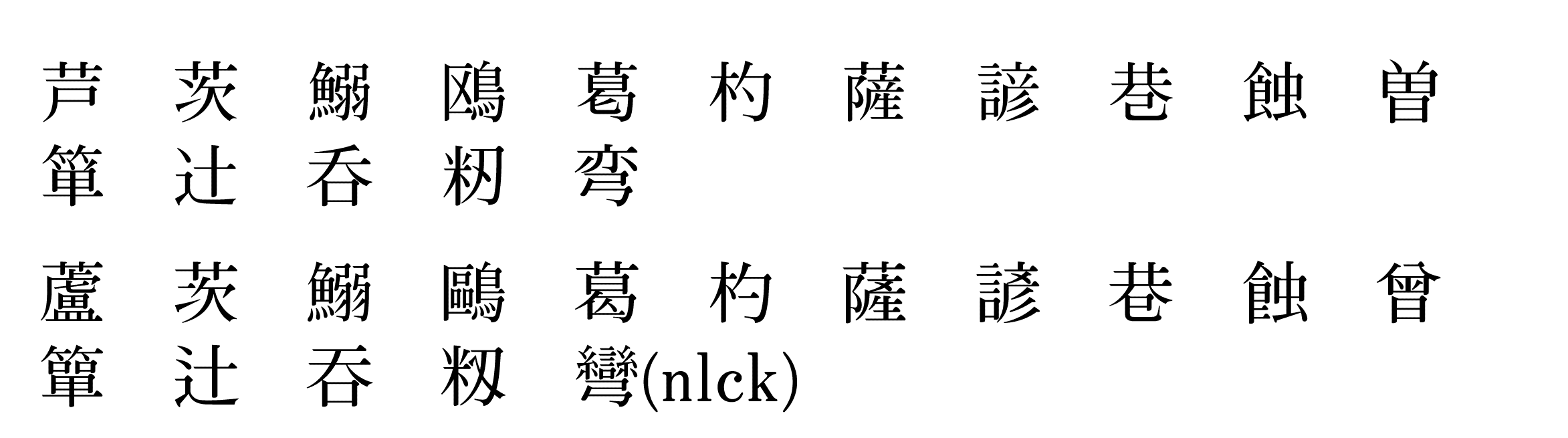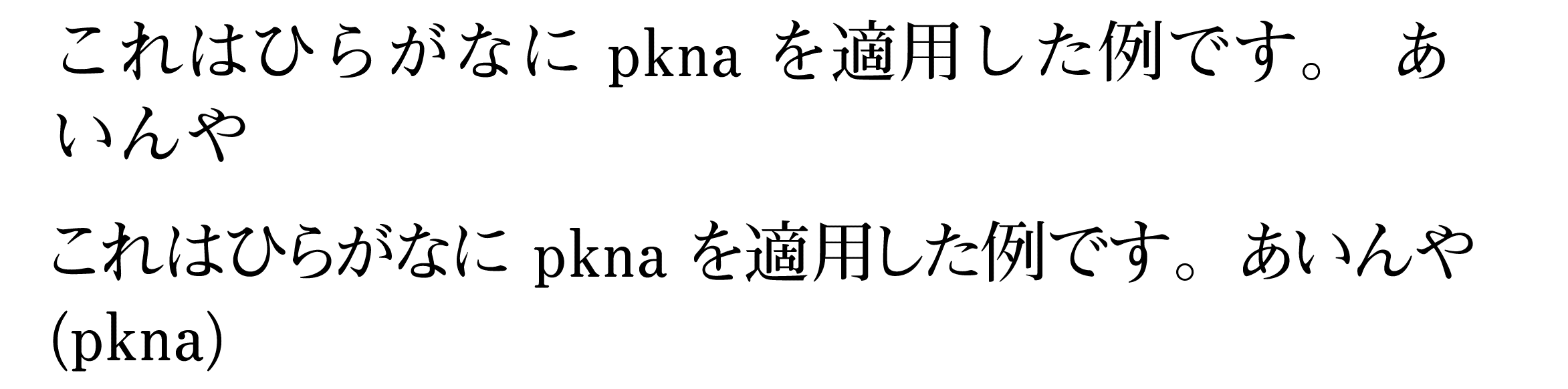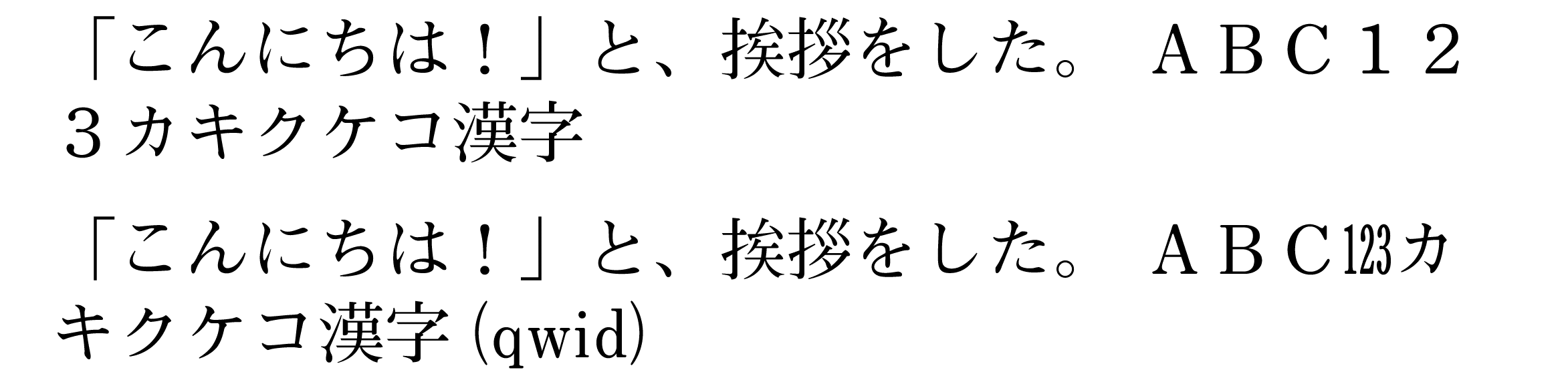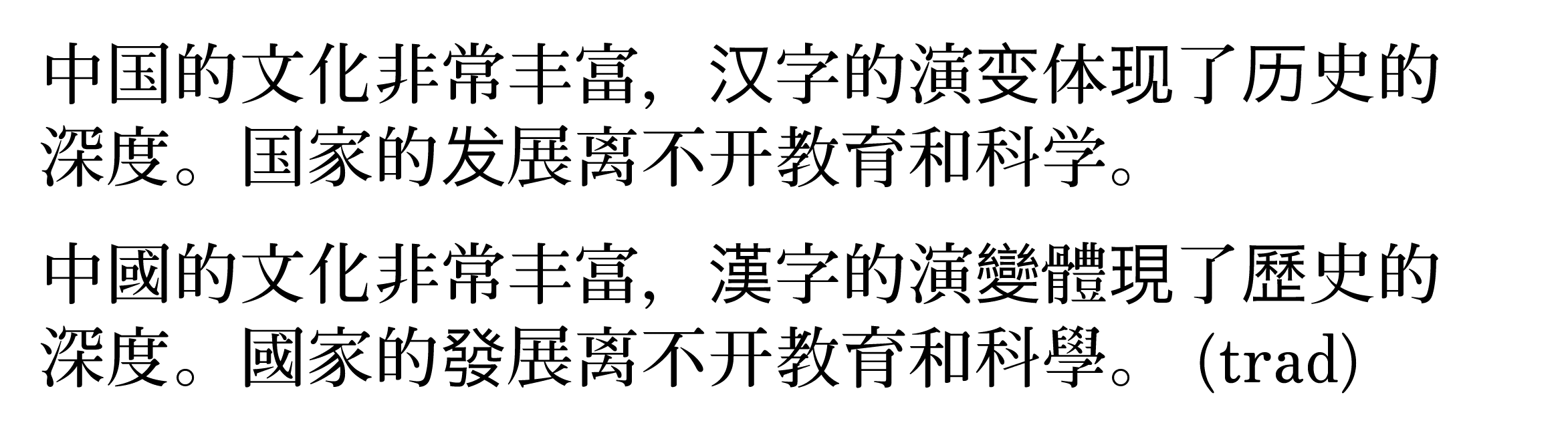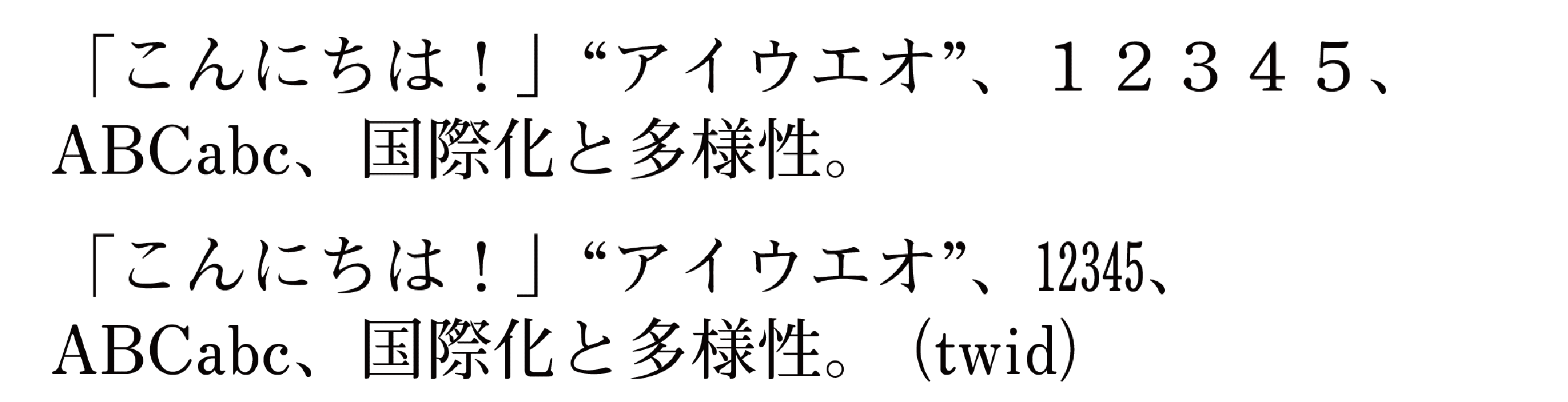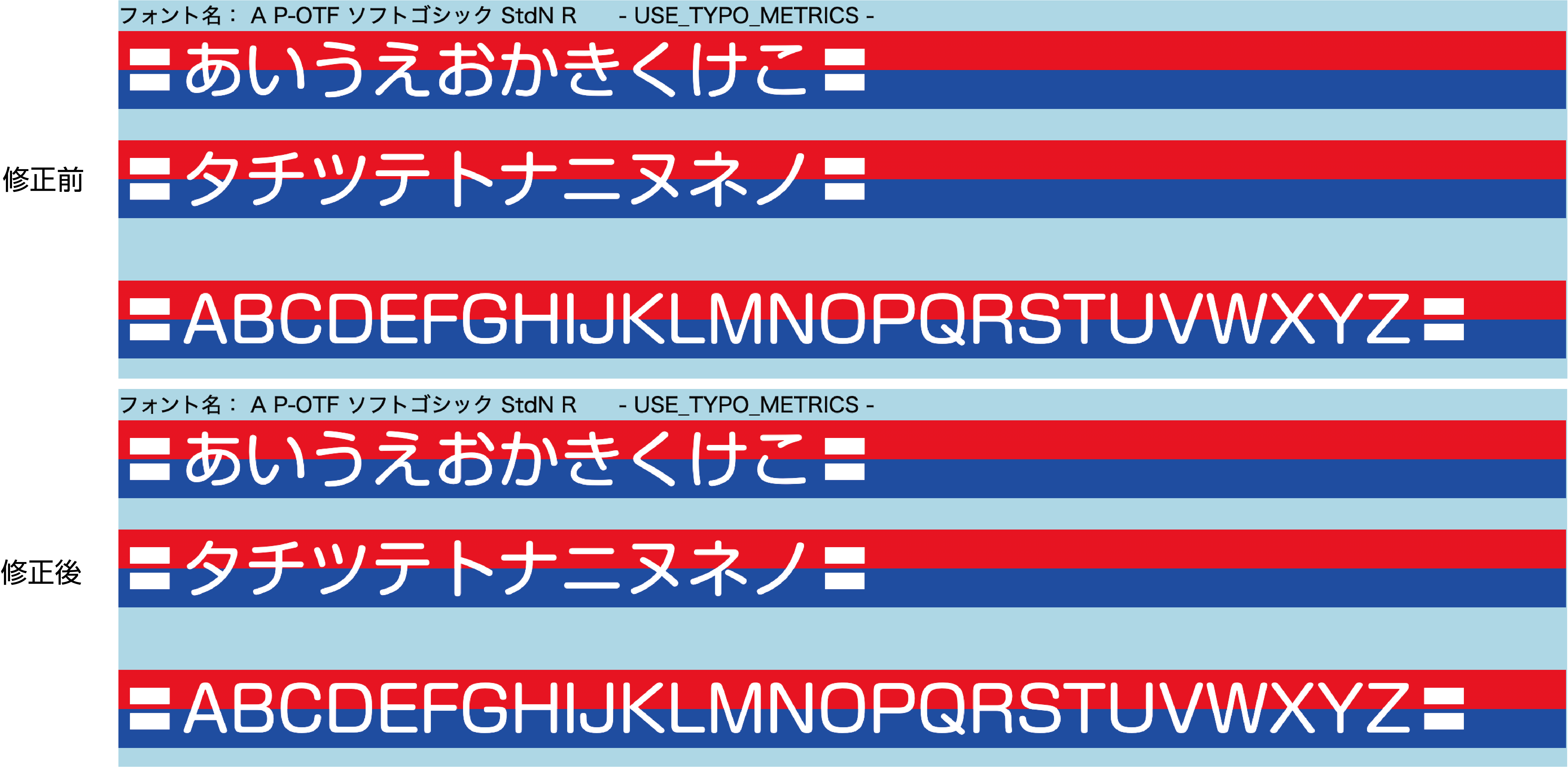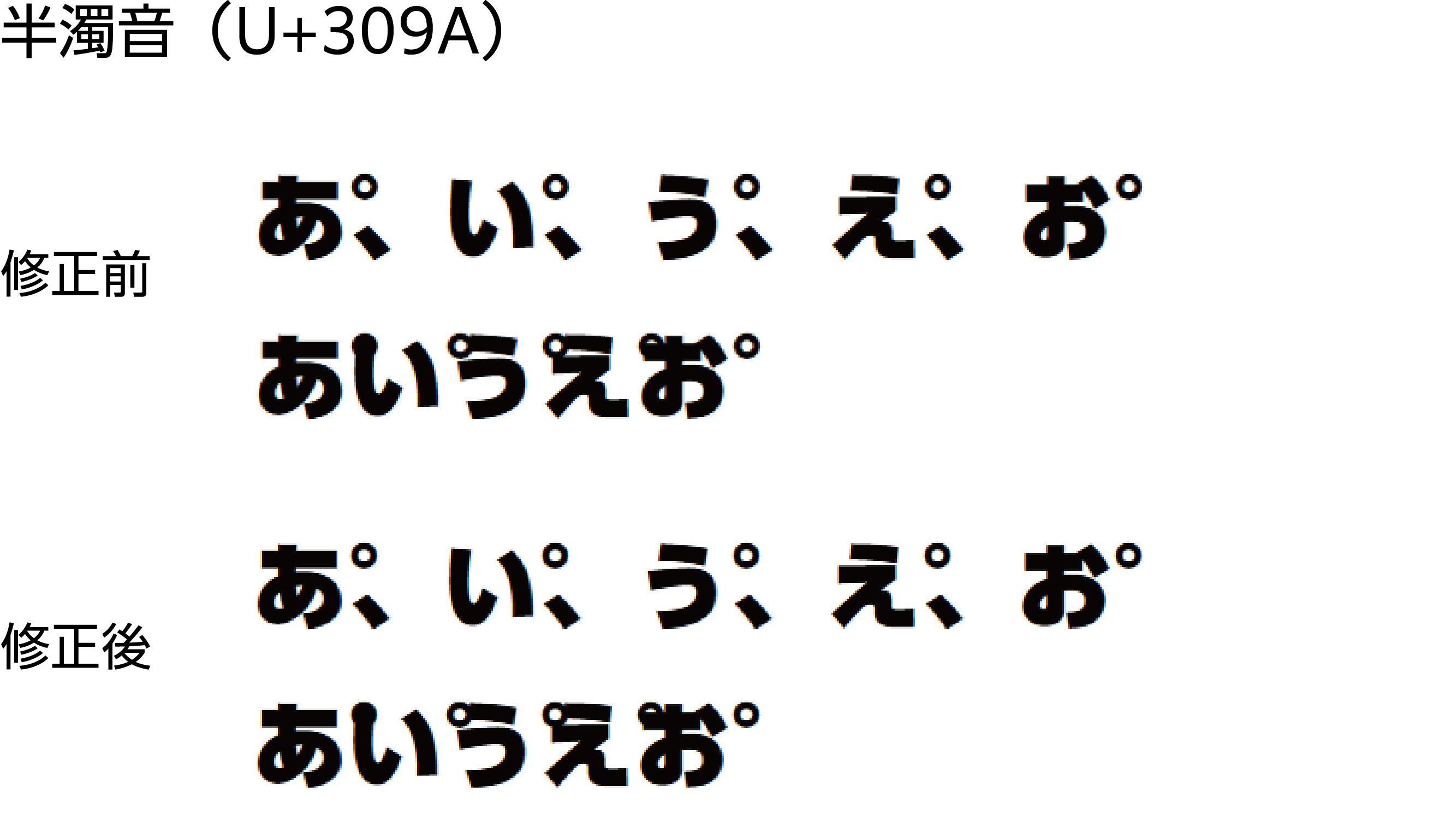
Morisawa Fonts Webフォントの5つの機能をアップデートしました。
なお、本アップデートの機能は一部のフォントのみ適用されます。
- 主要OS間での行間・文字位置の統一
- 文字間トリミング(text-spacing-trim)の改善
- アンダーラインの描画の改善
- 濁音・半濁音記号の表示改善
- GSUB機能の拡張
アップデート内容
【1】主要OS間での行間・文字位置の統一
日本語・中国語・韓国語に対応したフォントにて、WindowsとMacでテキストの上下の位置が異なる問題の修正を行いました。
WindowsでWebフォントを表示した際に、Macで表示した時よりも文字が上や下にずれて見えていたため、修正を行いました。
これによりWindowsとMacのどちらでも同じ位置に文字が表示されます。
<Windows>
<Mac>
【2】文字間トリミング(text-spacing-trim)の改善
和文フォントにおいて、括弧類と句読点類の間でツメ処理が働かない問題の修正を行いました。なお、text-spacing-trimに対応していないブラウザでは解消されません。
CSSのtext-spacing-trim機能を使用した際、括弧類と句読点類が隣り合う場合にツメ処理が適用されなかった問題があったため、修正を行いました。
<修正前>
<修正後>
【3】アンダーラインの描画の改善
和文フォント(漢字を含むフォント)において、Chromium系ブラウザでゼロ幅スペース「ZWSP」[U+200B]を使うと、アンダーラインが一部欠ける問題の修正を行いました。
漢字を含む和文フォントをChromium系のブラウザで使用した際、ゼロ幅スペース(ZWSP:U+200B) を入れると、一部の アンダーライン(下線)が途中で切れてしまう問題の修正を行いました。
<修正前>
<修正後>
【4】濁音・半濁音記号の表示改善
濁音「゛」(U+3099)や半濁音「゜」(U+309A)が本来付かない仮名文字と組み合わせた場合に、Chromium系ブラウザでフォントが適用されない問題の修正を行いました。
本来は濁音(U+3099)や半濁音(U+309A)がつかない仮名文字に濁音・半濁音を付けた際に、文字が正しく表示されない問題の修正を行いました。
濁音と半濁音はPr5以上の文字セットに収録されています。
※半濁音では、濁音を使用した場合のような問題は見られませんでしたが、濁音と同じ処理を行っています。
【5】GSUB機能の拡張
30種類のOpenTypeの字形置換機能(GSUB)を拡張しました。
画像(上段:アップデート前 下段:アップデート後)
1. afrc
スラッシュで区切られた数字を、代替の積み重ね分数形式 に変換
※分母・分子ともに1桁の必要があります。
2. dlig
任意の合字
※フォントに含まれないグリフは変換されません
3. dnom
数字やスラッシュを、分数用の分母グリフに置換
4. expt
エキスパート字形への置き換え
※フォントに含まれないグリフは変換されません。
5. frac
スラッシュで区切られた数字を斜線による分数に置き換え
6. fwid
等幅全角字形(全角)への置き換え
7. hkna
標準のかなを、横書き専用にデザインされた字形に置き換え
※本機能は縦書き用の字形を横書き用に置き換える機能です。
8. hojo
補助漢字を含む字形への置き換え
※フォントに含まれないグリフは変換されません
9. hwid
等幅半角字形(半角)への置き換え
※漢字などは変化しません。
10. ital
欧文字形を対応するイタリック字形に置き換え
※英文・半角の約物のみがイタリックになります。
11. jp04
JIS2004 規格の日本語字形への置き換え
※フォントに含まれないグリフは変換されません。
12. jp78
JIS C 6226-1978(JIS78)規格の日本語字形への置き換え
※フォントに含まれないグリフは変換されません。
13. jp83
JIS X 0208-1983(JIS83)規格の日本語字形への置き換え
※フォントに含まれないグリフは変換されません。
14. jp90
JIS X 0208-1990(JIS90)規格の日本語字形への置き換え
※フォントに含まれないグリフは変換されません。
15. lnum
数値字形をライニング数字に置き換え
16. nalt
代替注釈形式
17. nlck
印刷標準字体への置き換え
※フォントに含まれないグリフは変換されません。
18. numr
数字やスラッシュを、分数用の分子グリフに置換
19. onum
数値字形をオールドスタイル数字に置き換え
20. pkna
「かな」および「かな」関連の字形セットにおいて、プロポーショナル字形への置き換え
21. pwid
プロポーショナル字形への置き換え
22. qwid
等幅四分字形への置き換え
※フォントに含まれないグリフは変換されません。
23. ruby
ルビ用字形を有効化
24. sinf
プレーンなHTMLサブとスーパーとは異なり、同じフォントの太さと定義済みの位置を使用し、下付きにする
25. subs
下付き文字に置き換える
26. sups
上付き文字に置き換える
27. trad
中国語簡体字または日本語の漢字において、旧字体への置き換え
※フォントに含まれないグリフは変換されません。また、旧字体がないものは変化いたしません。
28. twid
等幅三分字形への置き換え
29. vkna
標準のかなを、縦書き専用にデザインされた字形に置き換え
※本機能は横書き用の字形を縦書き用に置き換える機能です。
30. zero
0の数字を斜線付きの0に置き換え